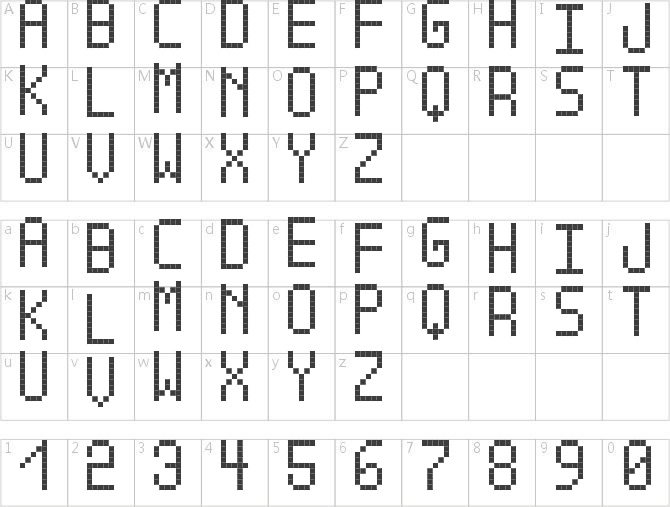
Cross-led-tfb-bold 詳情頁
字體名稱: Cross-l
Cross-led-tfb-bold
Cross-led-tfb-bold介紹
Cross-led-tfb-bold字體字庫是一款讓人賞心悅目、百看不厭的英文字體,適合各類廣告和產品包裝設計應用,字體大小0.09MB,格式為ttf字體,上傳用戶是瀨子,作者/版權方為未知
Cross-led-tfb-bold效果圖